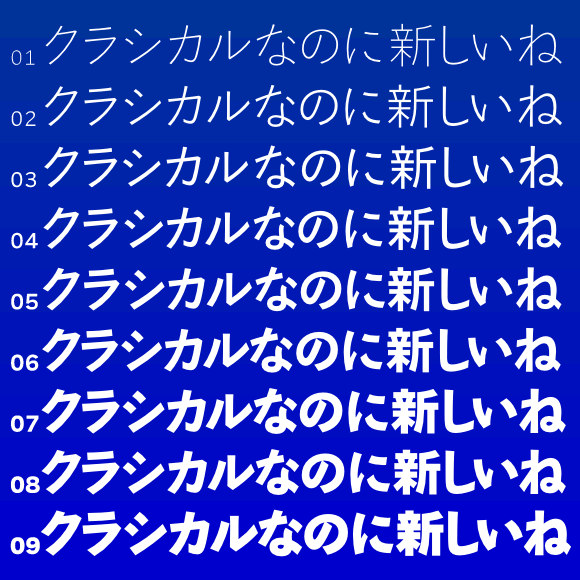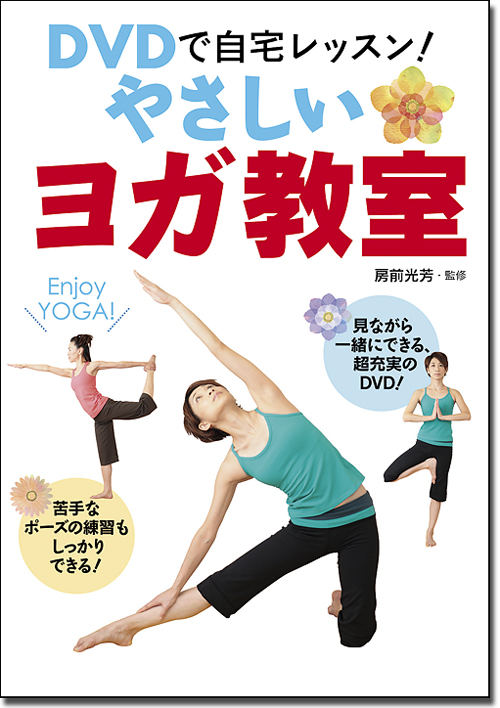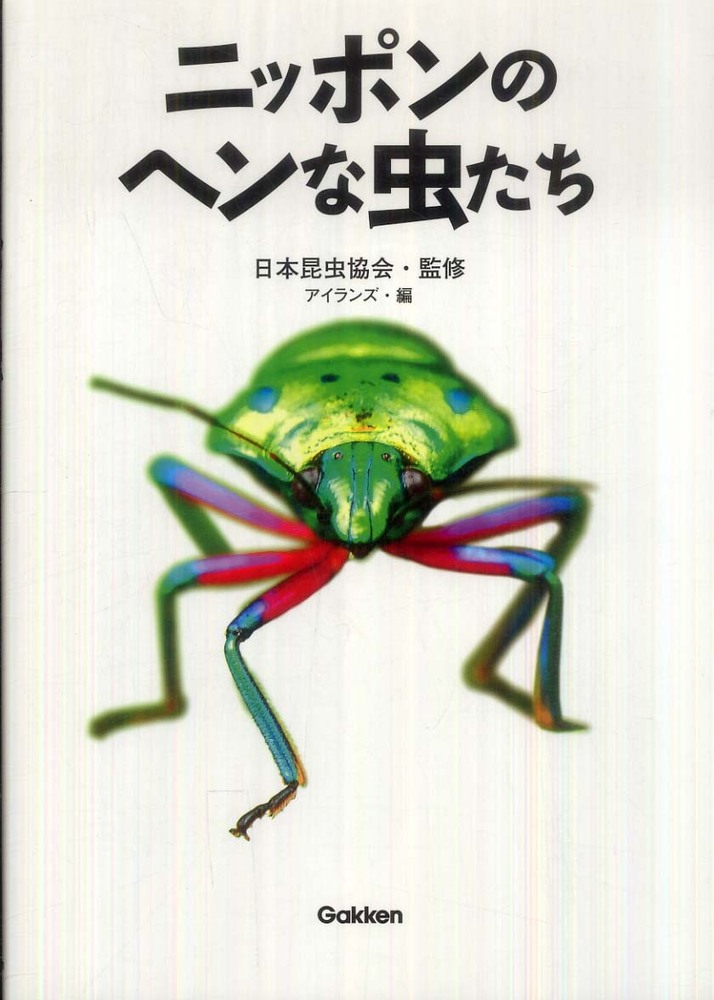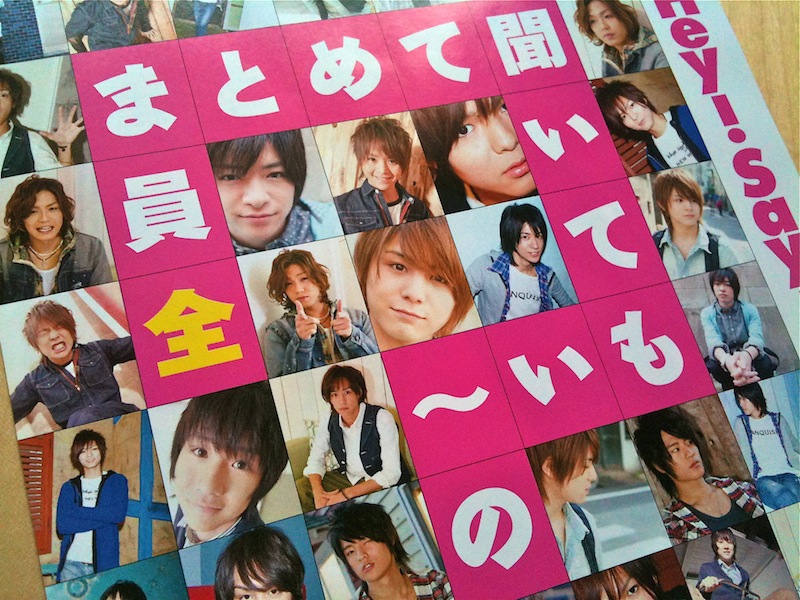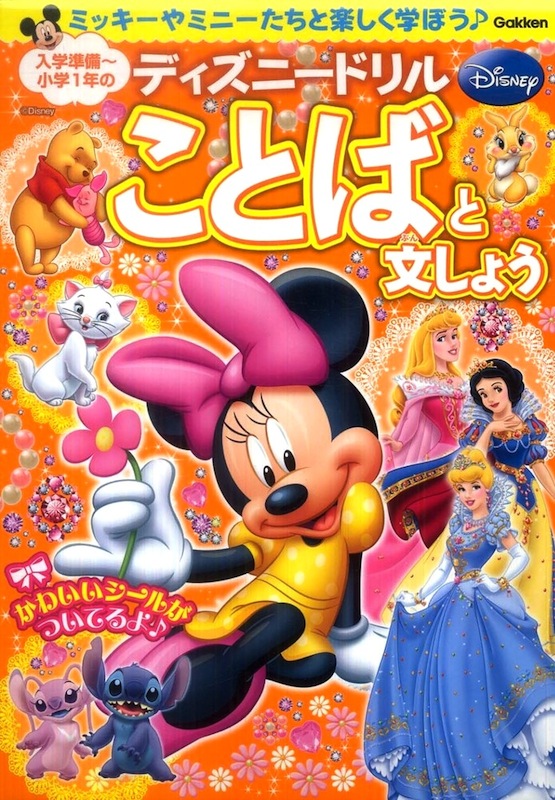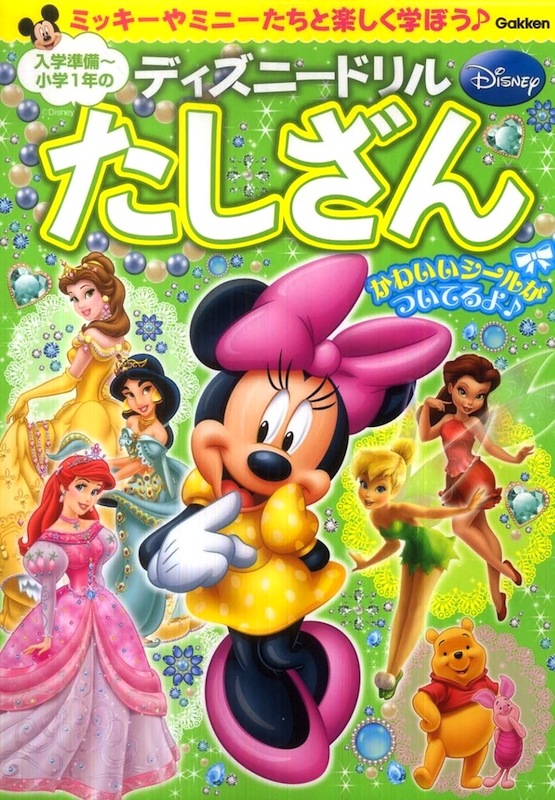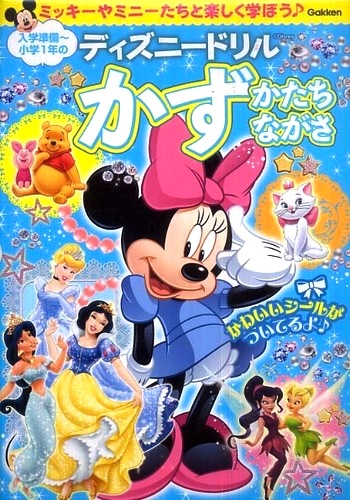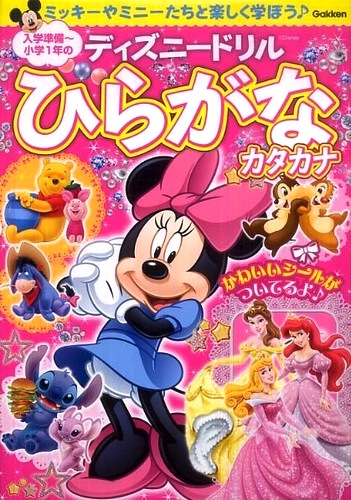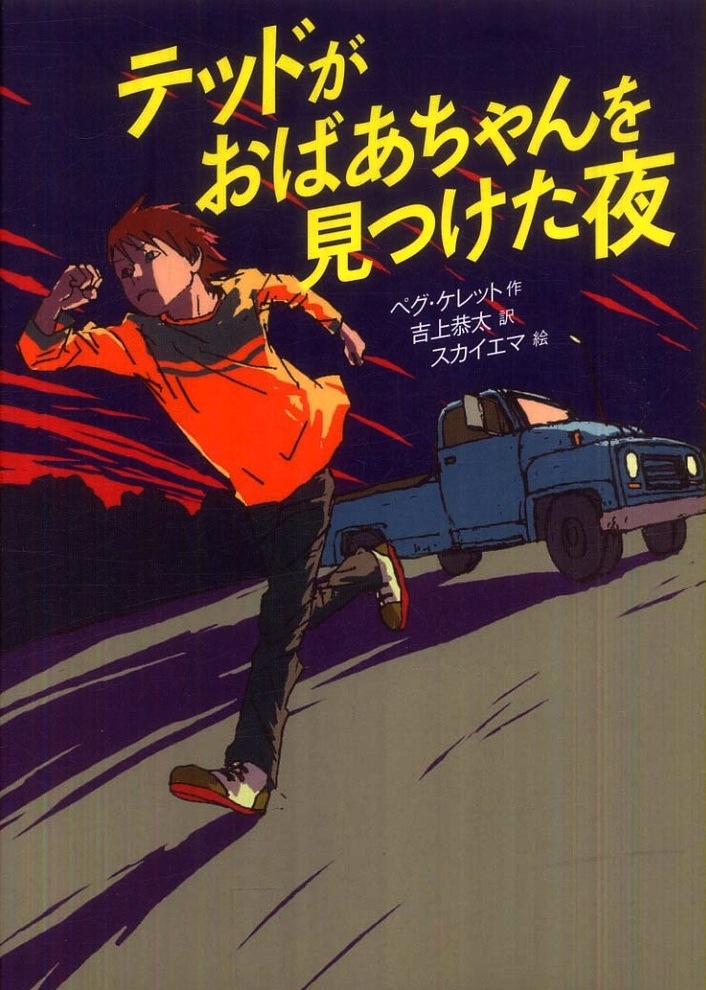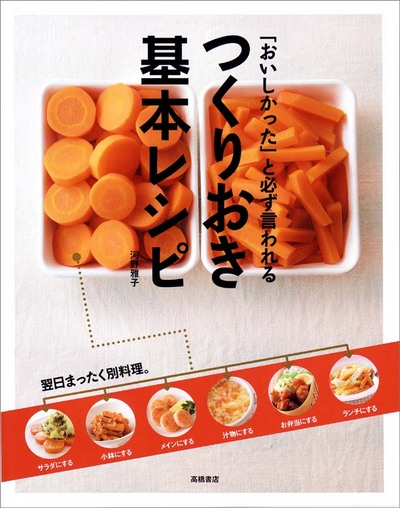
大阪通天閣のみやげ品売り場で。
CDやDVDのレンタルシステムが使っている封筒。
書名:「ものづくり」でリハビリ実践ガイド
著者:畠山真弓
発行:学習研究社
山田玲司がビッグコミックスピリッツに連載中の「美大受験戦記 アリエネ」という漫画の扉ページ。
グラフィック処理されて角が丸くなっているが、間違いなく墨東書体。
これは新聞広告。
書名:「頭のいい人」は、シンプルに仕事する!
著者:中島 孝志
発行:三笠書房
こちらが本の表紙。
墨東ルイカでサイネージを作成しました  KASE  2012年4月2日(月) 16:26
先日購入しました墨東ルイカを使用したサイネージ画像を投稿します。
ロケーションは虎ノ門にある共同通信会館のエレベータホールおよび地下にある休憩スペースになります。
記事データを自動処理し、文章、写真を合成・画像化する仕組みになっています。
以前はルイカを使っていたのですが、少し印象が固いという声があったため今回墨東ルイカを使用しました。
配色も落ち着いていて、いい感じですね。
KASEさまから送られてきた、他のニュース画像も掲載します。
もう1点。
書名:太らないおかず142
発行:角川マガジンズ
世界各地の地名に墨東が使用されています。
書名:タビトモ〜
発行:JTBパブリッシング
文字の角が丸くグラフィック加工されています。
書名:ニットマルシェ
発行:日本ヴォーグ社
書名:ザ・タロット
著者:藤森 緑
発行:説話社